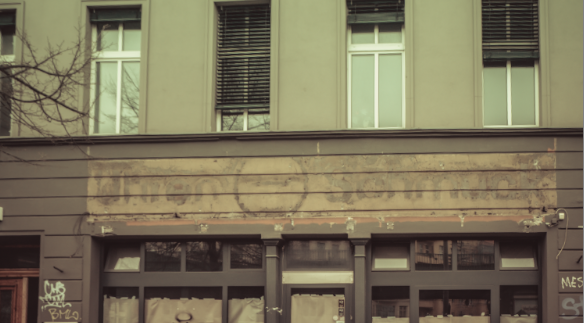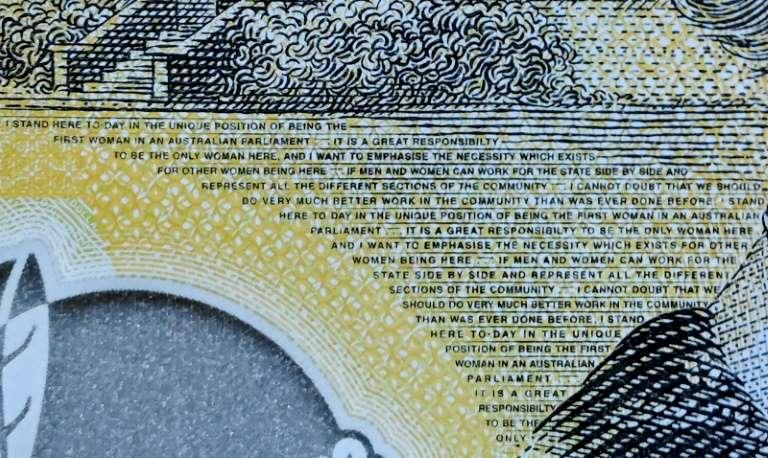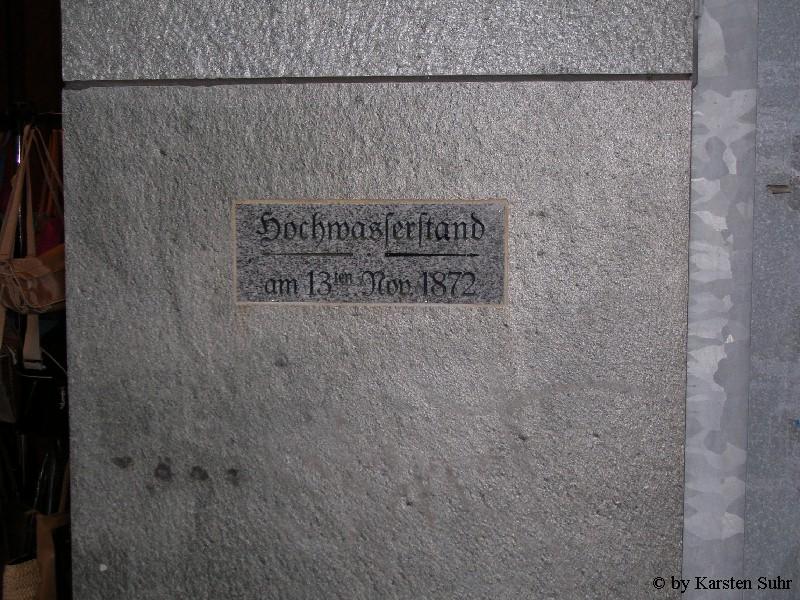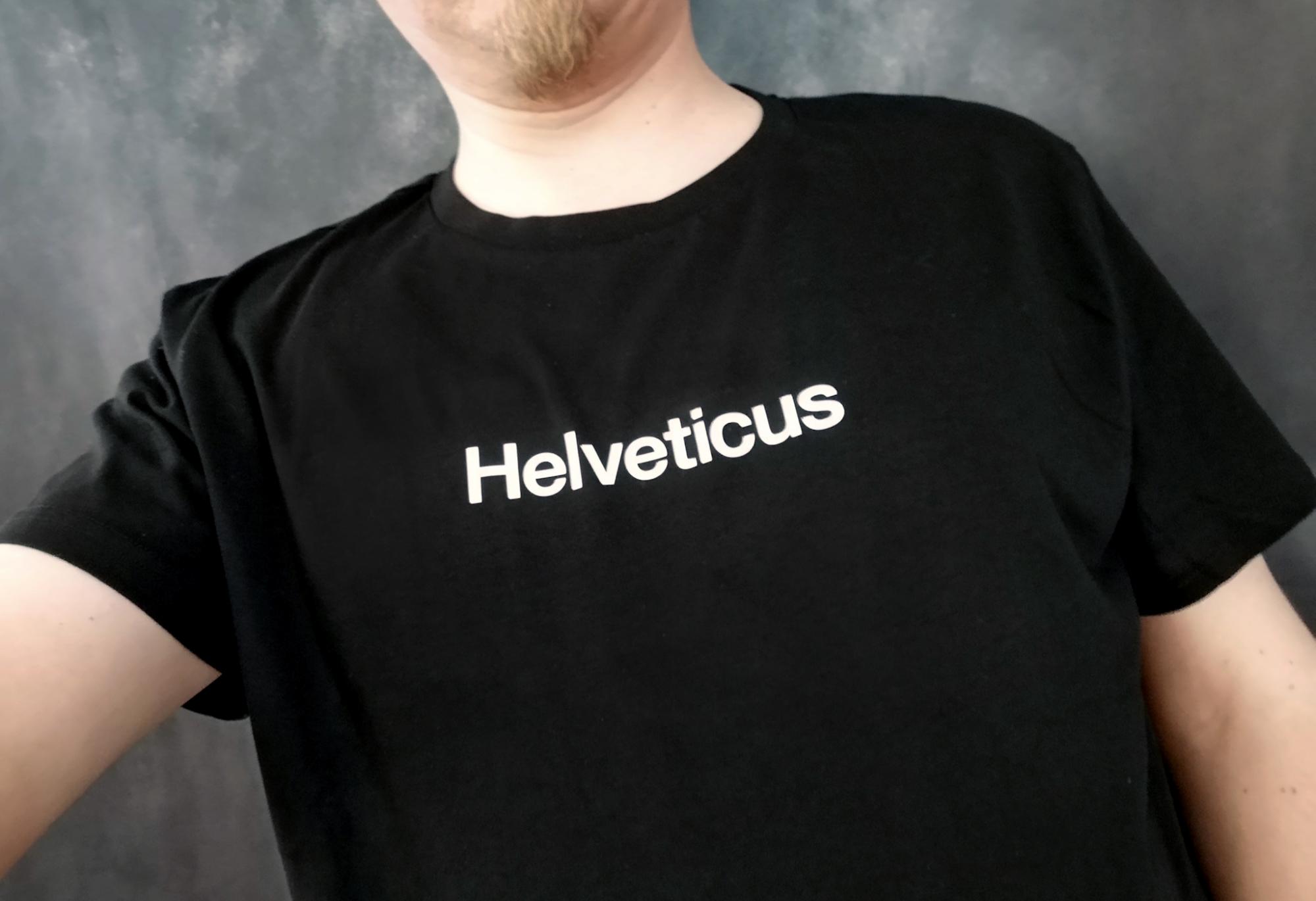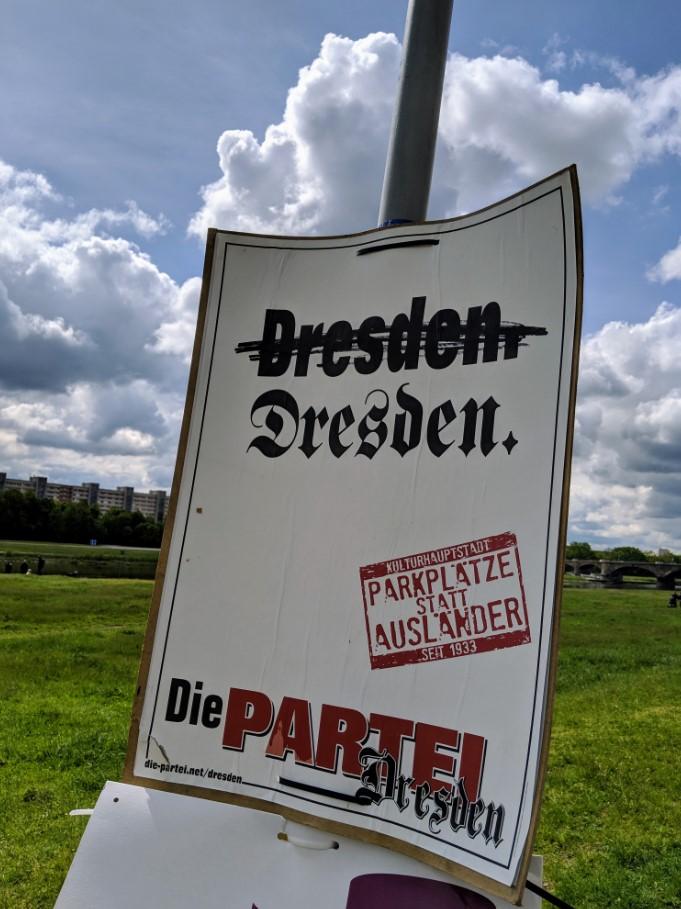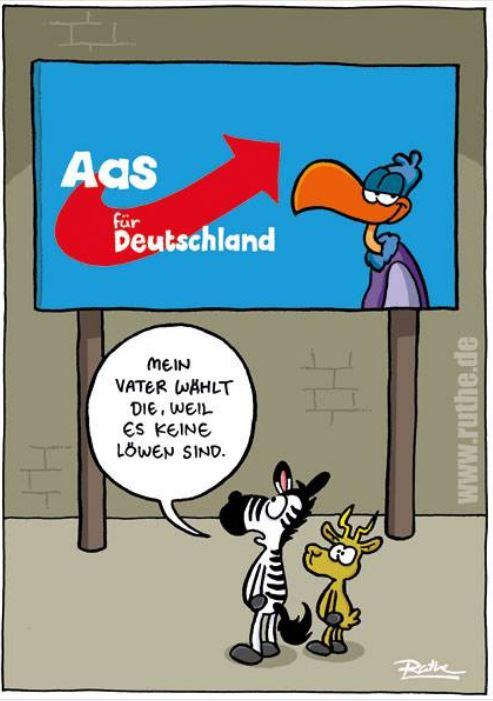
Die Friz Quadrata hat keines, das gezeigte ist ein kleines ß.
Ups. Dann ist das aber ein schon fast erwachsenes kleines Eszett :-P
Noch ist er ja Comic Sans … :party:
Als Schweizer geht das. Ich habe einen eigenen kleinen Schneideplotter, Aufbügelfolie und ein Bügeleisen – und so habe ich mir dieses Späßchen erlaubt. :-)
Was nicht alles im Verborgenen schlummert.
das war vor der Wende ein Uhren & Schmuck Laden
Berlin, Schönhauser Allee
Ich fürchte fast, dass die Satire da für viele zu subtil sein dürfte.
Wenn da nicht Die PARTEI stehen würde, wäre ich mir wohl selbst nicht 100%ig sicher.
Würde mich nicht wundern, wenn irgendwann der Slogan PARKPLÄTZE STATT AUSLÄNDER von Rechtsextremen kopiert und übernommen wird :baeh:. Wäre ein Thema für extra3 dann :-)
Bernd Höcke macht das bestimmt :hammer:
Ich fürchte fast, dass die Satire da für viele zu subtil sein dürfte.
Wenn da nicht Die PARTEI stehen würde, wäre ich mir wohl selbst nicht 100%ig sicher.
Was genau ist dort subtil :-? Ich sehe nur einen Holzhammer …
Glaubst du wirklich, dass sowohl Schrift als auch Aussage für DEN Dresdner normal/alltäglich/vertretbar/wünschenswert sind? :shock:
Ich bin da mittlerweile auch vorsichtiger geworden – was für den einen völlig absurd ist, nehmen manche für voll.
Ich fürchte fast, dass die Satire da für viele zu subtil sein dürfte.
Wenn da nicht Die PARTEI stehen würde, wäre ich mir wohl selbst nicht 100%ig sicher.
100%ig sicher das was? Dresden braucht dringend Parkplätze! 😆
Glaubst du wirklich, dass sowohl Schrift als auch Aussage für DEN Dresdner normal/alltäglich/vertretbar/wünschenswert sind?
DEN Dresdner gibt es natürlich nicht. Die Dresdner, die ich am besten kenne, sind »ultralinksgrüne« Hippies aus der Neustadt.
Ich lebe aber auch den größten Teil des Jahres in einem Land mit sehr stolzer, bisher ungebrochener republikanischer Tradition 🇺‍🇸, in dem sowohl der Regierungschef als auch die Hälfte des Parlaments und des politischen Spektrums sich von vielen demokratischen Normen praktisch über Nacht verabschiedet haben.
Und ich lebe mehrere Monate im Jahr in einem deutschen Bundesland 💛🖤, in dem Weimarer Verhältnisse herrschen, es also keine 100%ig den demokratischen Grundwerten der Republik verpflichtete parlamentarische Opposition¹ mehr gibt.
Das geht also schneller als man denkt mit dem Verfall demokratischer Werte. Und gerade Trump hat gezeigt, dass Millionen von Wählerı̊nnen Kandidaten selbst dann wählen, wenn sie deren Slogans für zu extrem halten (aber mögen, dass einer die da oben mal ordentlich provoziert). Dresdner Wählerı̊nnen könnten sich also durchaus von diesem eigentlich absurden Slogan angesprochen fühlen (und eine rechtsextreme Partei wählen, die ihn ernsthaft plakatiert), selbst wenn sie nicht der Meinung sind, Flüchtlinge seien buchstäblich weniger wert als Parkplätze.
1. Nix gegen Bodo Ramelow und die vielen, vielen wunderbaren einer toleranten Demokratie verpflichteten Linken. Aber wegen des starken Putin verherrlichenden Flügels gilt das eben leider nicht für die gesamte Partei.
Hier ging es rein um die Gestaltung vom Plakat.
Ist da die  Partei gemeint,die "immer Recht"  hatte. Oder ist die jetzt neu??
Solch ein Schreibfehler kann aber auch durchaus ein Sicherheitsmerkmal sein, denn ein Fälscher, der nicht wirklich Buchstabe für Buchstabe vergleicht, könnte diesen Text dann richtig schreiben, und dabei eben übersehen, das auf dem Originalgeldschein da ein i fehlt.
Ich hatte hier zuerst gefragt wie ich einen mißratenen Beitrag löschen kann. Kann ich (noch) nicht.
Damit dieser Beitrag Sinn erhält, hier ein Link zu einem Buch. Nicht gerade ein Fundstück, weil ich lange danach gejagt habe, aber vielleicht doch unterhaltsam:
1. Wir sind hier ziemlich Stußresistent, und immer bereit Stuß zu verzeihen, wenn das Forenmitglied dies einsieht und geradestellt.
2. Auch nach längerer Zeit können Förderer dieses Furums ihre Beiträge bearbeiten, und so Stuß bereinigen.
3. Nicht selten enthält Stuß durchaus interessante Ideen, die sich lohnen, weiter verfolgt zu werden.
4 Auch ich habe sicherlich so einigen Stuß verfasst also alles wirtd gut...